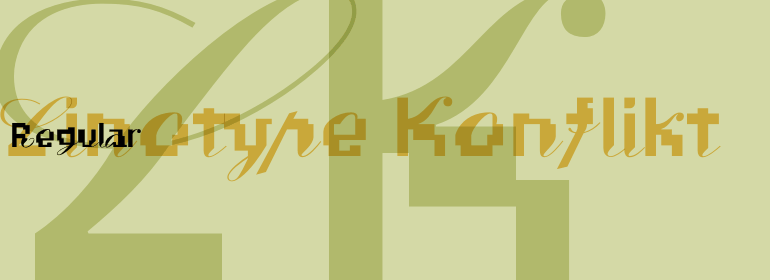
Linotype Konflikt™
Linotype Konflikt™,这款字体结构工整、笔画清晰,兼顾美观与易读性,适用于标题、正文、海报、包装、LOGO 等多种场景。字形优雅稳定,风格百搭耐看,适配日常排版与创意设计,让文字呈现更舒适、更具质感。Linotype Konflikt™一笔一画,皆是细节,以均衡的比例、流畅的线条打造舒适视觉体验,字形端正大气,风格简约现代。无论是商业设计、品牌宣传还是日常排版,都能轻松驾驭,让文字更有格调与力量。Linotype Konflikt™字体下载。
字体品牌: Linotype(Monotype) 设计师:Pott,Stefan 字体分类:衬线体 字体属性:外文 字符集:Unicode 发布时间: 2018